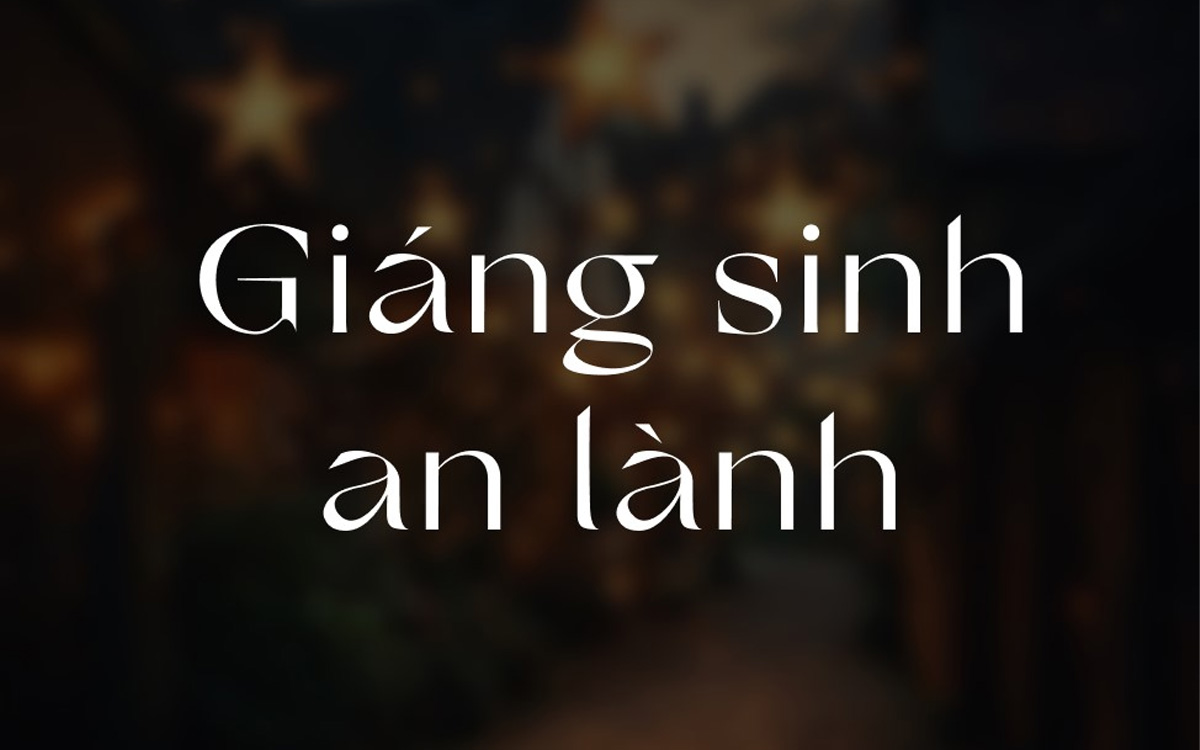
Font chữ thanh lịch, hiện đại, sang trọng dùng cho thiết kế thiệp cưới, thời trang, tạp chí SVN- GrandSlang
Trong thế giới thiết kế đồ họa đương đại, phông chữ không đơn thuần là công cụ thể hiện văn bản mà còn là linh hồn tạo nên diện mạo thị giác đẳng cấp và khác biệt cho mọi sản phẩm truyền thông. Bộ font chữ thanh lịch, hiện đại, sang trọng SVN-GrandSlang ra đời như một giải pháp typography vượt trội, đáp ứng trọn vẹn những chuẩn mực khắt khe nhất của nghệ thuật chữ viết cao cấp. Với khả năng ứng dụng linh hoạt và thẩm mỹ tinh tế, SVN-GrandSlang đã trở thành sự lựa chọn hàng đầu cho các nhà thiết kế trong lĩnh vực thiệp cưới, thời trang xa xỉ và các ấn phẩm tạp chí nghệ thuật.</p>
Font Chữ Thanh Lịch, Hiện Đại, Sang Trọng Dùng Cho Thiết Kế Thiệp Cưới, Thời Trang, Tạp Chí SVN-GrandSlang
SVN-GrandSlang là bản Việt hóa hoàn chỉnh của typeface GrandSlang nổi tiếng, một phông chữ sở hữu phong cách Serif Tân Cổ Điển (Neoclassical Serif) pha trộn nét Calligraphy quyến rũ và hơi thở đồ họa đương đại. Được nghiên cứu và việt hóa tỉ mỉ bởi đội ngũ SVN, phông chữ này giữ nguyên vẹn cái hồn của bản gốc đồng thời tối ưu hóa hoàn hảo bộ dấu tiếng Việt, giúp các designer dễ dàng sáng tạo mà không gặp bất kỳ rào cản kỹ thuật hay lỗi hiển thị nào.
Điểm đặc trưng của SVN-GrandSlang nằm ở độ tương phản nét thanh nét đậm vô cùng mạnh mẽ, tạo nên cảm giác kiêu kỳ, cuốn hút ngay từ cái nhìn đầu tiên. Nhờ sự cân bằng hoàn hảo giữa tính cấu trúc kỹ thuật và nét mềm mại quyến rũ, phông chữ này mang đến vẻ đẹp không tuổi, vừa đậm chất hoài cổ lại vừa vô cùng tân tiến. Đây chính là chìa khóa vàng cho những dự án đang tìm kiếm sự độc bản, nâng tầm giá trị thương hiệu lên một đẳng cấp mới.
1. Đường Nét Thiết Kế Tinh Tế, Kết Hợp Giữa Calligraphy Cổ Điển Và Hình Học Hiện Đại
SVN-GrandSlang sở hữu ngôn ngữ thiết kế vô cùng đặc biệt với sự hòa quyện giữa nghệ thuật viết chữ tay truyền thống và các khối hình học hiện đại. Mỗi ký tự đều được chăm chút kỹ lưỡng về mặt tỷ lệ, tạo nên sự hài hòa tổng thể khi đứng cạnh nhau trong mọi bố cục:
• Độ tương phản nét vượt trội: Sự đối lập giữa nét chính dày dặn, vững chãi và nét phụ siêu mảnh mang lại hiệu ứng thị giác mạnh mẽ, thu hút ánh nhìn của người xem ngay lập tức.
• Chân chữ (Serif) sắc sảo: Thiết kế chân chữ dạng nét thẳng hiện đại kết hợp với các đường cong uốn lượn mềm mại ở phần đầu và đuôi chữ, tạo cảm giác thanh thoát nhưng vẫn giữ được sự chắc chắn.
• Cấu trúc chữ độc đáo: Các chữ cái được tạo hình phá cách, thoát khỏi các quy chuẩn thông thường để mang lại trải nghiệm thị giác mới lạ, đậm chất nghệ thuật đương đại.
2. Bản Việt Hóa Chuẩn Tối Ưu Cho Ngôn Ngữ Tiếng Việt
Một trong những thách thức lớn nhất khi sử dụng các font chữ nước ngoài trong thiết kế tiếng Việt là bộ dấu thường làm hỏng tổng thể thẩm mỹ của chữ. SVN-GrandSlang đã giải quyết hoàn toàn vấn đề này nhờ quy trình Việt hóa chỉn chu và tỉ mỉ:
• Dấu thanh được tinh chỉnh hài hòa: Các dấu sắc, huyền, hỏi, ngã, nặng và các dấu mũ được thiết kế lại với độ mảnh và góc nghiêng đồng bộ tuyệt đối với thân chữ, không gây cảm giác chật chội hay đứt gãy.
• Khoảng cách ký tự (Kerning) chuẩn xác: Hệ thống kerning tiếng Việt được tối ưu hóa giúp các từ ghép khi đứng cạnh nhau luôn giữ được nhịp điệu mượt mà, tự nhiên và dễ đọc.
3. Giải Pháp Typography Hoàn Hảo Cho Thiết Kế Thiệp Cưới Sang Trọng
Thiệp cưới là nơi lưu giữ những khoảnh khắc trọng đại nhất của đời người, đòi hỏi sự chỉn chu, lãng mạn và quý phái. SVN-GrandSlang đáp ứng trọn vẹn mọi mong muốn của các cặp đôi và nhà thiết kế thiệp cưới chuyên nghiệp:</p>
Phông chữ này vô cùng thích hợp để thể hiện tên chú rể – cô dâu, các tiêu đề chính như “Save the Date”, “Thiệp Mời”, hay bộ chữ lồng (Monograms) cá nhân hóa. Khi kết hợp với các kỹ thuật in ấn cao cấp như ép kim vàng (gold foil), dập nổi (embossing) trên chất liệu giấy mỹ thuật cao cấp, SVN-GrandSlang sẽ tỏa sáng rực rỡ, mang đến vẻ đẹp vừa lãng mạn vừa đậm chất hoàng gia hiện đại.
4. Định Hình Thần Thái Đẳng Cấp Cho Thương Hiệu Thời Trang Ca Cao Cấp
Trong ngành công nghiệp thời trang và mỹ phẩm xa xỉ, typography đóng vai trò cốt lõi trong việc thể hiện cái tôi và định vị vị thế thương hiệu. SVN-GrandSlang chính là “vũ khí bí mật” dành cho các nhà thiết kế logo, bao bì và bộ nhận diện thương hiệu thời trang:
Với dáng vẻ sang trọng và thời thượng, font chữ này thường được sử dụng cho logo của các nhà thiết kế thời trang, nhãn mác quần áo, bao bì nước hoa, son môi hay các bộ sưu tập Lookbook mùa mới. Vẻ đẹp kiều diễm của SVN-GrandSlang giúp sản phẩm nhanh chóng ghi dấu ấn sâu sắc trong tâm trí khách hàng, khẳng định giá trị thương hiệu thượng lưu và dẫn đầu xu hướng.
5. Sự Lựa Chọn Hàng Đầu Cho Thiết Kế Tạp Chí Và Ấn Phẩm Nghệ Thuật
Đối với các biên tập viên và nhà thiết kế dàn trang tạp chí (Editorial Design), việc chọn font chữ cho trang bìa và các tiêu đề lớn là yếu tố quyết định sức hút của ấn phẩm. SVN-GrandSlang mang đến hơi thở của những tạp chí thời trang cao cấp hàng đầu thế giới: